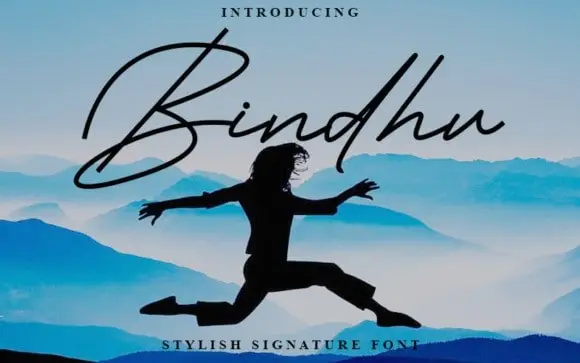
Bindhu Handwritten Font – Download Grátis
A fonte ‘Bindhu Handwritten Font’ é uma escolha perfeita para aqueles que buscam uma escrita cuidadosamente feita com personalidade. Inermedia STUDIO criou este recurso moderno e autêntico, projetado especificamente para variedades de usos, desde assinaturas elegantes até embalagens de produtos chamativas. Com sua estrutura completa de letras maiúsculas e minúsculas, números e pontuação, esta fonte não apenas atende a um amplo espectro de necessidades estéticas e funcionalas, mas também incorpora alternativas e caracteres internacionais. Suas linhas curvas fluídas e sua tipografia modernizada ainda manterão uma aura autêntica, tornando-a perfeita para aplicações que valorizam tanto a simplicidade quanto a individualidade de suas mensagens. O design da Inermedia STUDIO é ideal tanto para projetos de marca como para cartas de casamento e campanhas promocionais. Seja qual for o seu projeto, ‘Bindhu Handwritten Font’ proporcionará uma escrita única que refletirá a personalidade de sua marca em cada detalhe.